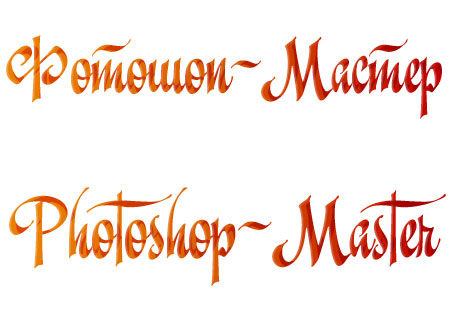
Дополнения Шрифты Татьяна Гапонова 26 апреля 2009 Шрифт - Christmas ScriptC Красивый шрифт для работы в Фотошоп с поддержкой русского языка. Скачать Шрифт - Christmas ScriptC
Классный шрифт, но больше похож на арабское начертание, нежели на новогоднее! =)
А оно что, всегда оранжевым пишет? о.О Красиво...